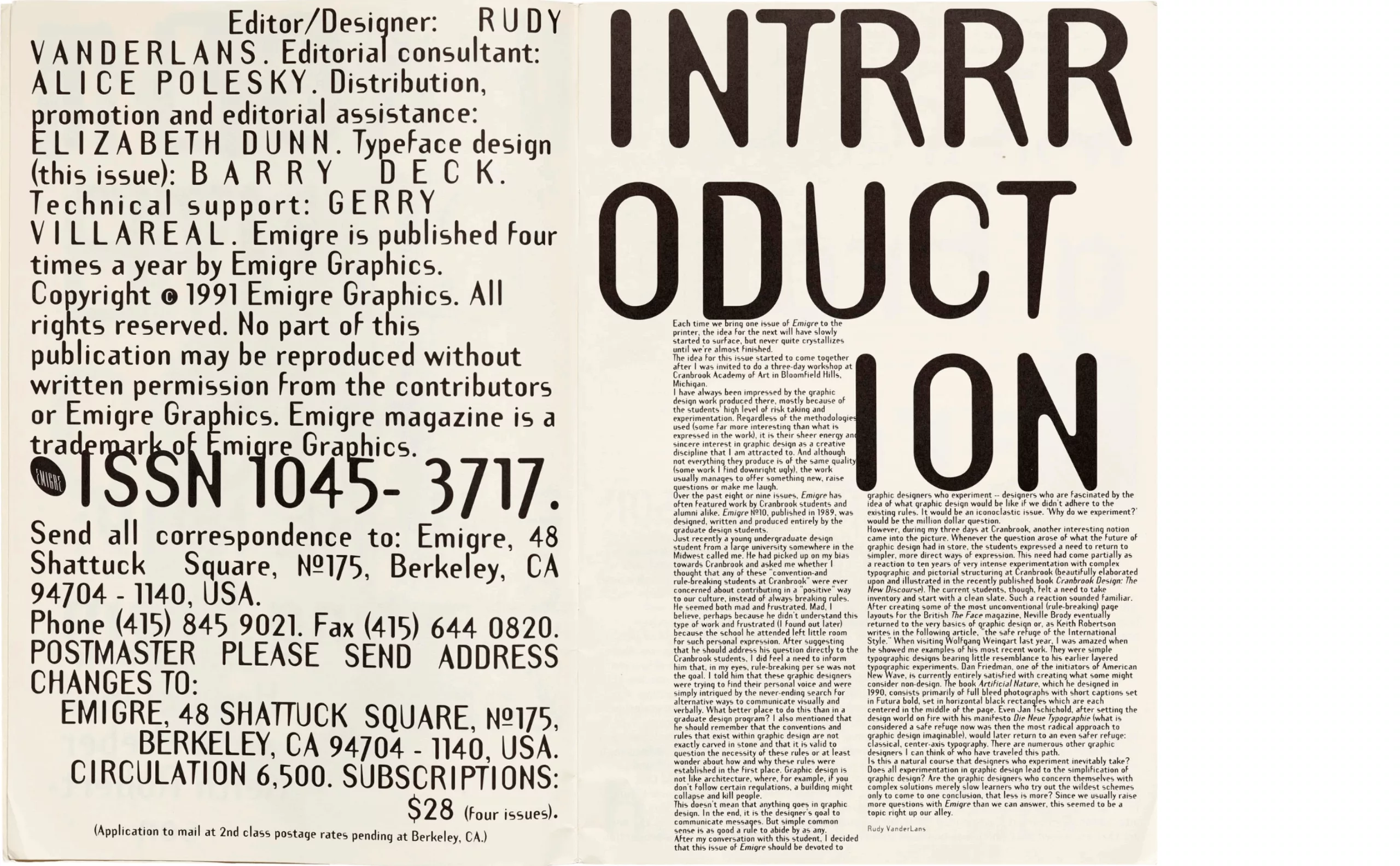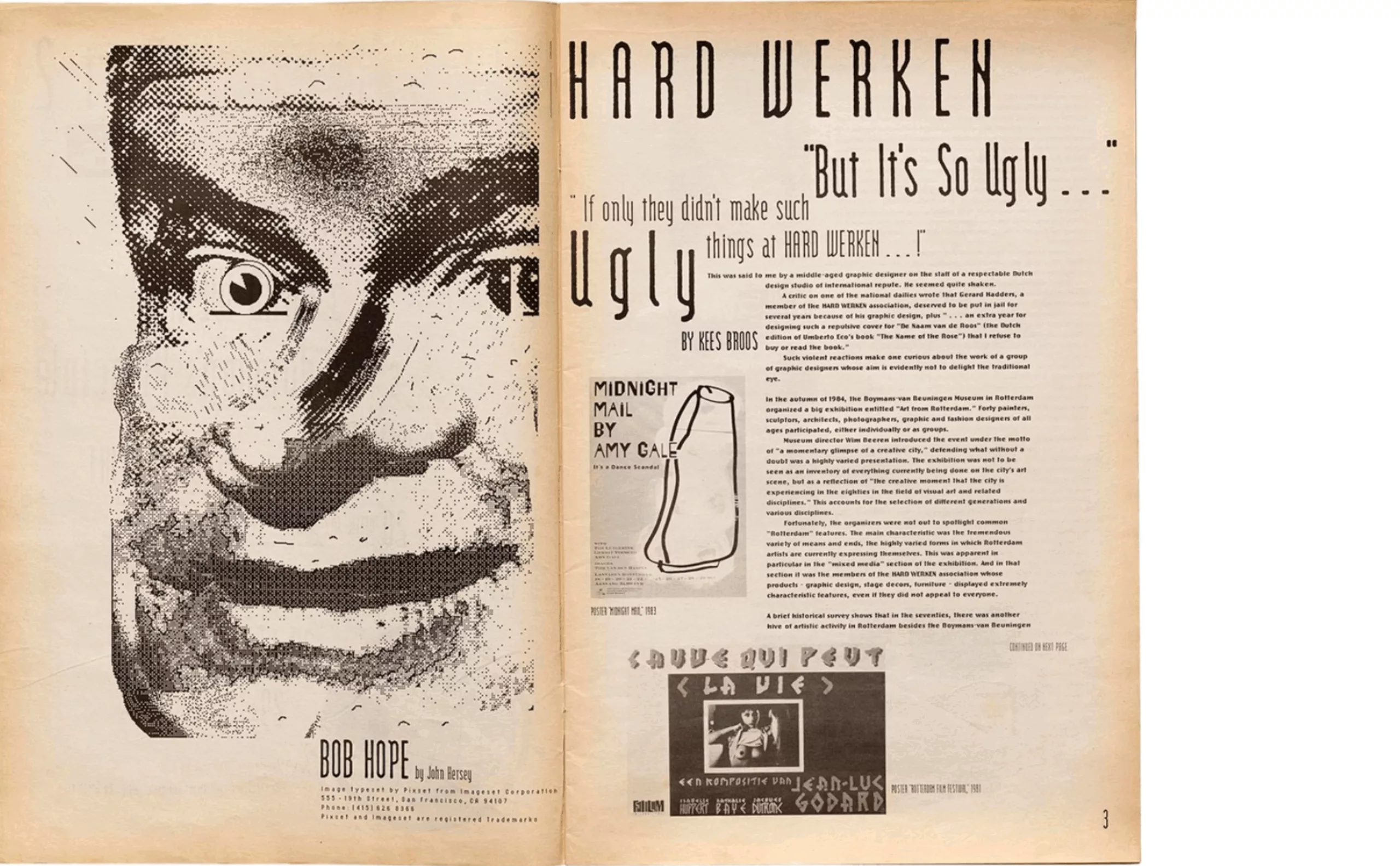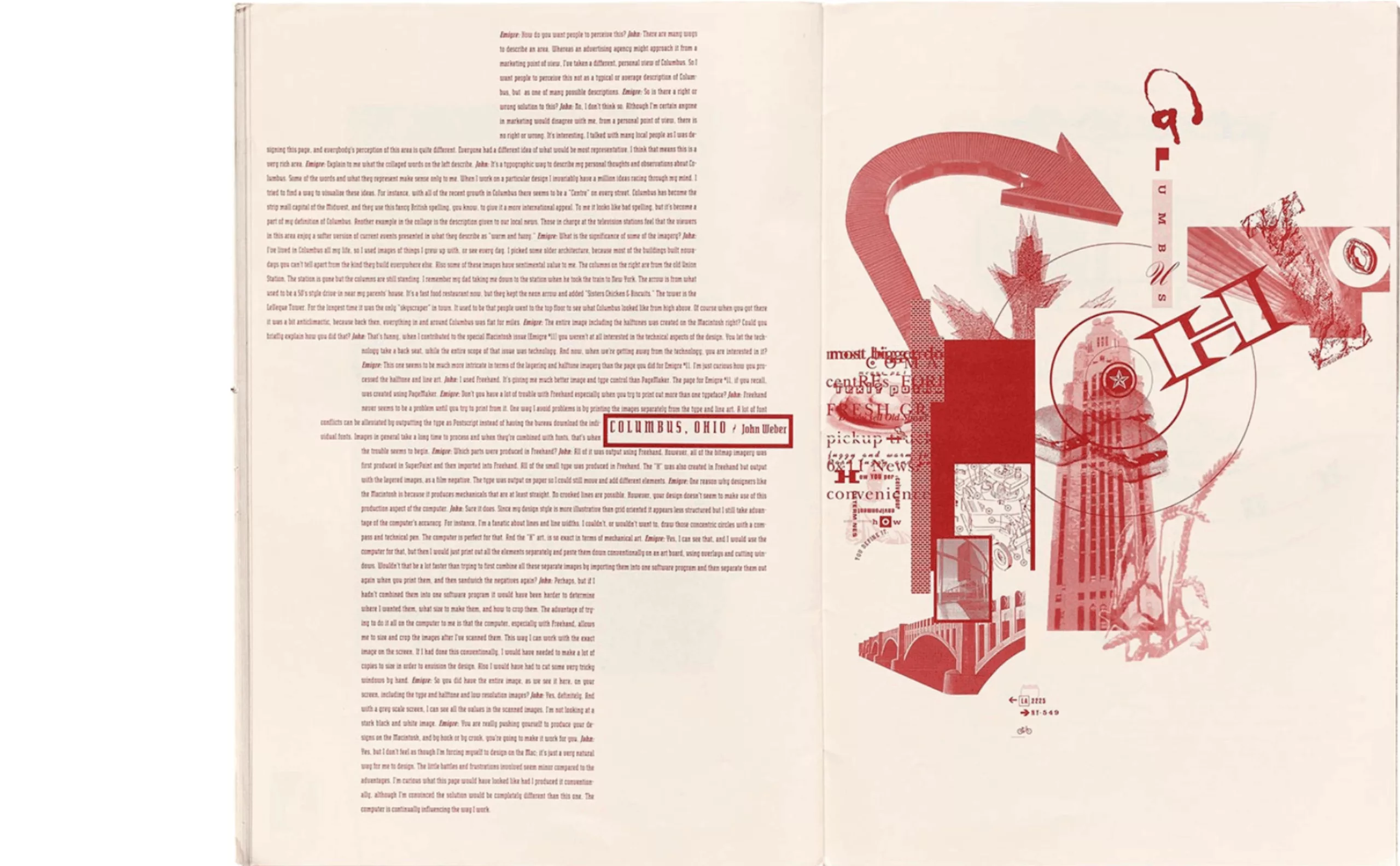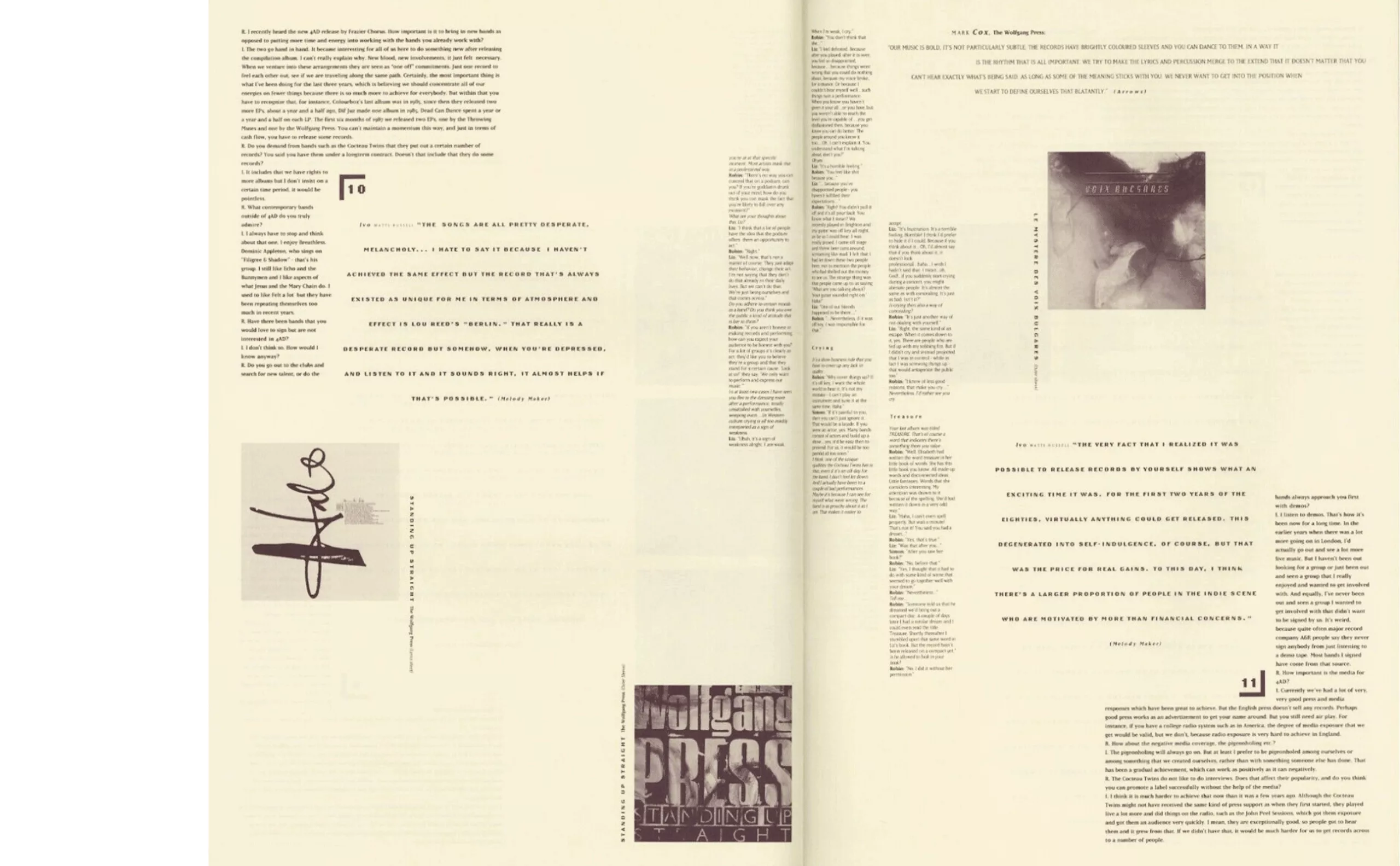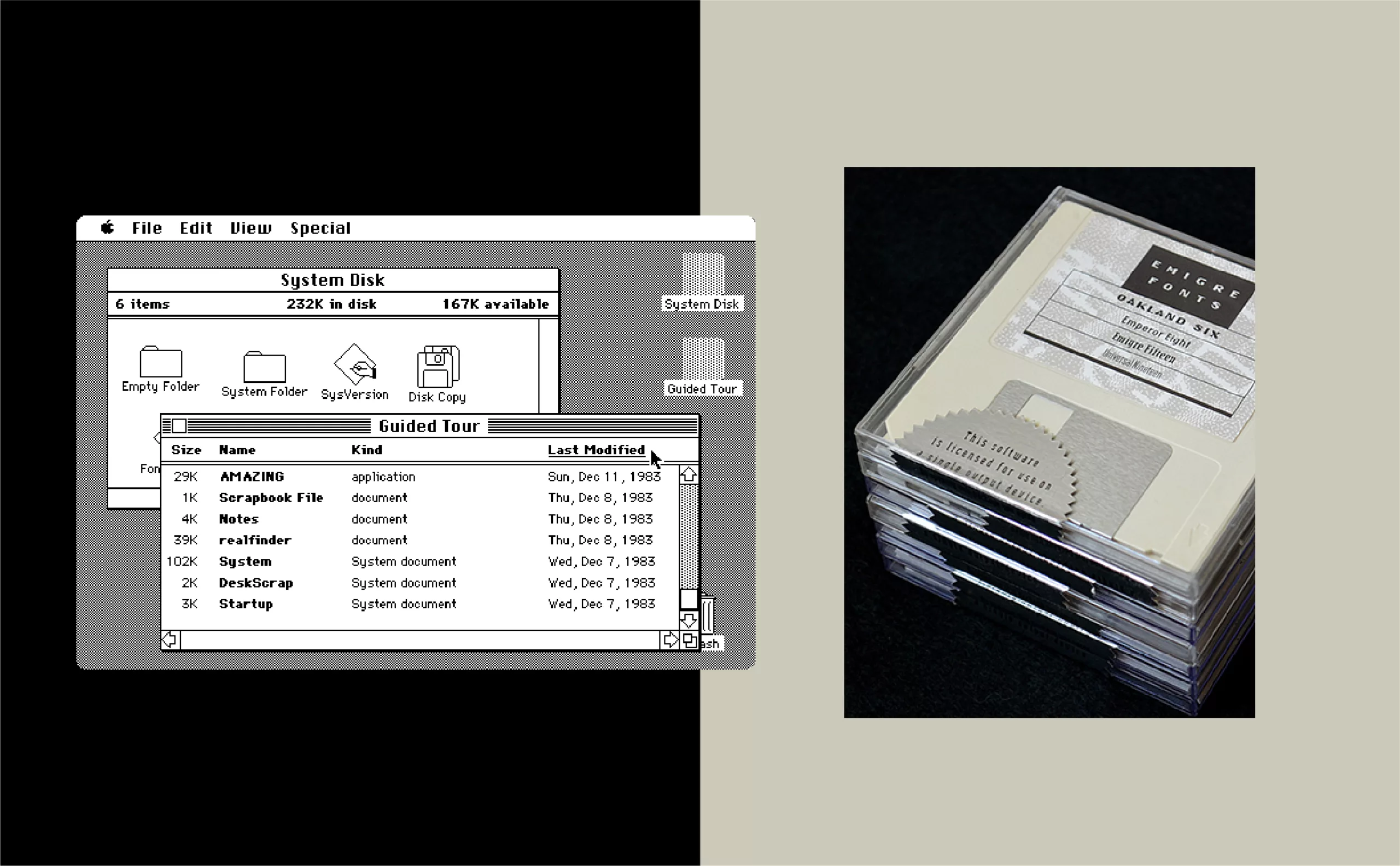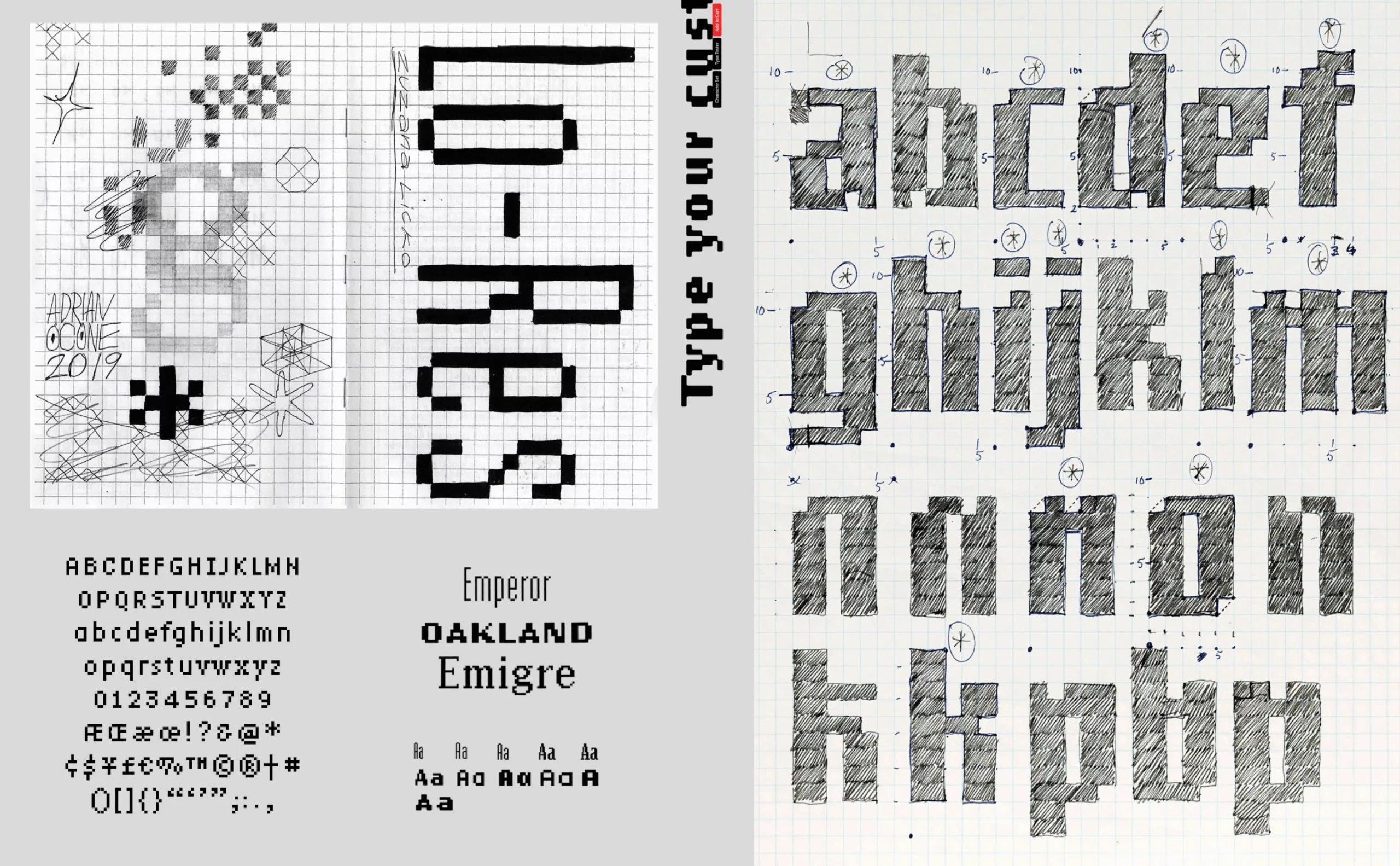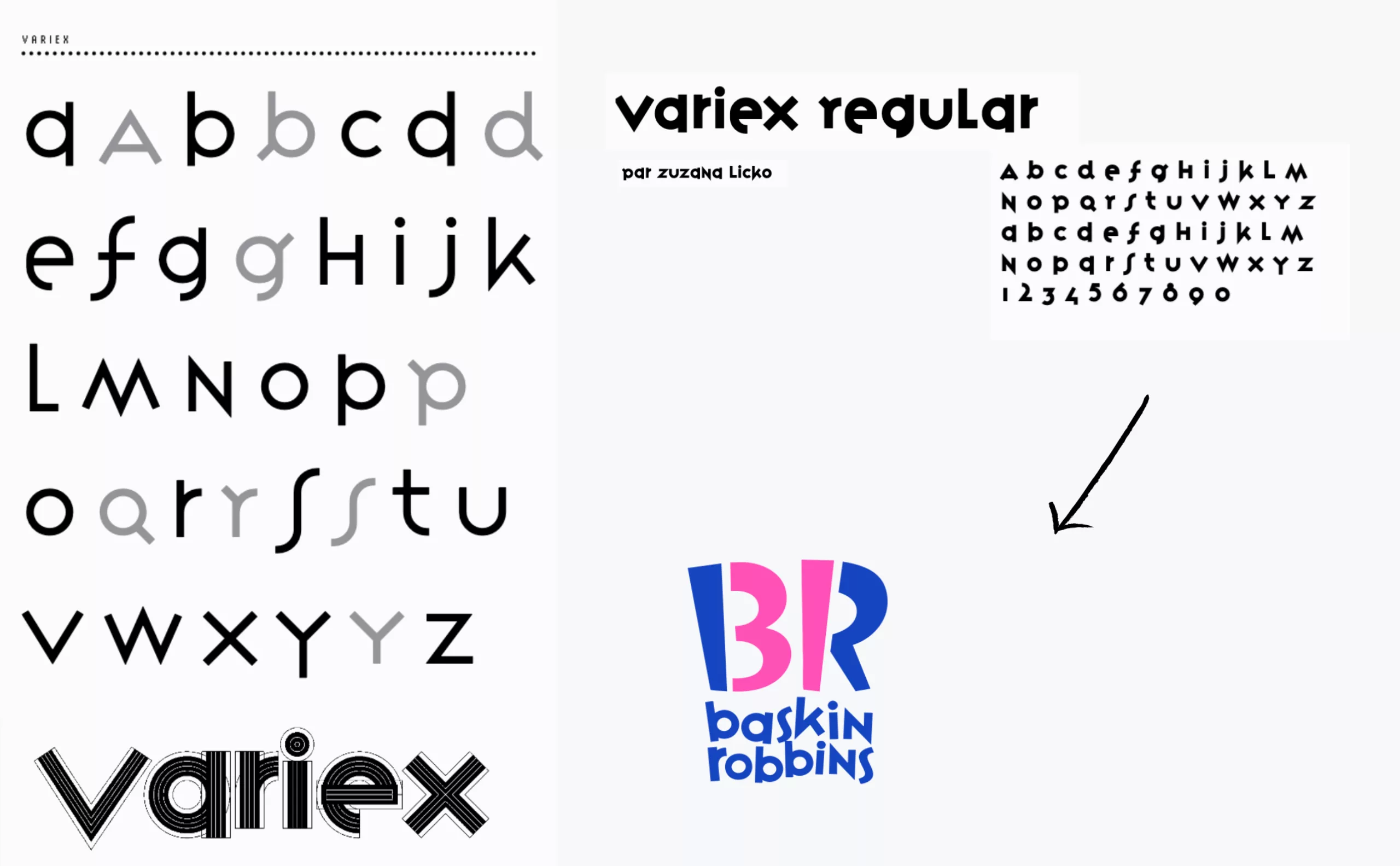
Zuzana Licko, pionnière de la typographie numérique
Dans les années 80 aux États-Unis, une femme américano-slovaque révolutionne le paysage de la typographie, et plus particulièrement de la typographie numérique : Zuzana Licko (née en 1961). Avant-gardiste, elle joue avec les pixels sur les premiers Mac et trace des caractères emblématiques.
1984, la révolution numérique ne fait que commencer
La révolution du numérique commence vraiment en 1984. Devenu mythique, le spot Apple de Ridley Scott, pastichant “1984” d’Orwell, ne sera diffusé qu’une seule fois devant 90 millions de téléspectateurs et téléspectatrices américaines : le 22 janvier, lors du troisième quart-temps du XVIIIe Super Bowl. La fin du film prophétisait : « Le 24 janvier, Apple Computer lancera le Macintosh. Et vous verrez pourquoi 1984 ne sera pas comme 1984 ! » Une athlète projetait une masse au milieu d’un écran dans un meeting de propagande.
La légende ne dit pas si Zuzana Licko a vu cette pub pour le Macintosh 128K (128 ko de mémoire vive !!!). Mais quelques mois plus tard, la plus célèbre designer de typographie numérique américaine va, elle aussi, faire voler en éclat la création de caractères typographiques, un domaine encore confidentiel, réservé à un petit cercle d’initiés.
Car à l’époque, rares sont les graphistes à s’embarquer dans l’aventure du numérique. En 1984, Zuzana Licko (que l’on prononce Litchko) va créer avec Rudy VanderLands (natif des Pays-Bas) une fonderie typographique devenue légendaire pour les 20 ans à venir, Emigre Graphics. La première fois que Zuzana Licko utilise un Macintosh c’est pour mettre en page Emigre Magazine lancé par son compagnon Rudy VanderLands et deux autres artistes néerlandais. Après quelques numéros, Emigre évolue d’un “Fanzine” artistique vers un support graphique expérimental et novateur. Tous deux diront que « la conception de caractères est un métier merveilleux qui nous permet d’exercer simultanément nos bizarreries personnelles, nos obsessions technologiques et notre patrimoine culturel. »
Chaque numéro est construit autour d’un thème unique. Tout est revisité et graphiquement personnalisé.
La photocomposition est alors encore coûteuse. C’est donc en “bricolant” directement sur un Mac “primitif” que Zuzana va explorer ces nouveaux territoires. « Lorsque j’ai commencé à créer des polices bitmap pour Macintosh en 1984, il s’agissait d’une entreprise purement expérimentale. Je n’avais pas de client pour ces polices et je n’avais pas non plus l’intention de développer une fonderie de caractères. C’est le magazine Emigre qui m’a ouvert ces possibilités. » Les caractères à basse résolution étaient imprimés sur une imprimante matricielle ImageWriter, pour être ensuite réduits à l’aide d’une caméra stat. Licko est une figure majeure du graphisme numérique aux côtés de Susan Kare, dont on parle dans cet article, qui s’attèle de son côté à créer les premières icônes et émojis pour humaniser les ordinateurs de l’entreprise à la pomme.
L’empire des typographies numériques d’Emigre magazine
Au milieu des années 80, l’usage de l’ordinateur était peu répandu et rares étaient les graphistes à s’aventurer sur ce que l’on commençait à appeler PAO (Publication Assistée par Ordinateur).
C’est petit à petit que la demande extérieure s’est faite plus précise. Des créateurs avant-gardistes, “post-moderne” comme David Carson vont se manifester. “Vendez-vous les polices originales que l’on trouve dans le magazine ?” C’est ainsi qu’est née la fonderie avec des polices sur disquette envoyées par la poste.
C’est par la diffusion du magazine et non par les circuits habituels de la reconnaissance, des concours et des prix que la visibilité et l’attrait du travail de Zuzana Licko et Rudy VanderLands vont se confirmer à l’international. Entrainant polémiques et jalousie. Toutes ces polices adaptées à la faible résolution des écrans et aux premières imprimantes seront par la suite regroupées dans la famille Lo-Res.
C’est l’époque où les grandes fonderies se contentaient souvent de numériser les caractères classiques. Pendant un certain temps, Emigre sera la seule fonderie à créer des caractères originaux pour Macintosh.
Puis à partir de 1989, d’autres dessinateurs de caractères numériques viendront rejoindre le duo. Ils seront une vingtaine à enrichir le catalogue. Barry Deck avec Arbitrary et Template Gothic, Jeffery Keedy et Keedy sans. Barry Deck traduit cet état d’esprit des origines. « Ce qui m’intéresse dans une police est qu’elle ne soit pas parfaite, précise. Une police qui reflète plus le langage imparfait d’un monde imparfait habité par des êtres imparfaits. »
Rapidement, Zuzana Licko va balayer d’un revers de main la question de la lisibilité de ses caractères bitmap. Une phrase est restée attestant le changement d’époque, «People read best what they read most. » « Les gens lisent mieux ce qu’ils lisent le plus » qui demeure sans doute, la seule règle à appliquer en ce qui concerne les paramètres culturels de la lisibilité d’un texte.
Après les polices bitmaps du départ, les polices vectorielles (Citizen, Matrix II, Totally Gothic) et les polices géométriques (Modula, Lunatix, Variex…) viendra le temps de polices plus sophistiquées, plus conceptuelles comme Triplex, une Humaniste sans serif plus conviviale que l’Helvetica. De nos jours, plusieurs logos utilisent les typographies de Zuzana Licko, comme les marques Shiva, mk2 et Baskin Robins qui font vivre les caractères Modula, Matrix II et Variex.
Pendant 23 ans de 1984 à 2005, Zuzana Licko et Rudy VanderLands vont publier 69 numéros d’Emigre Magazine qui demeure le témoin d’une période débordante de créativité.